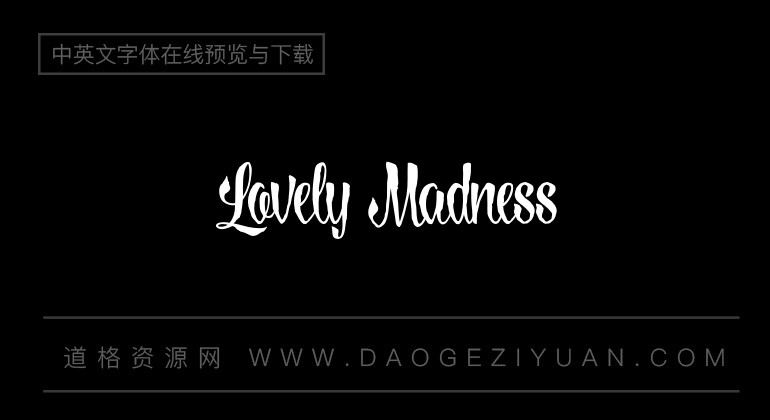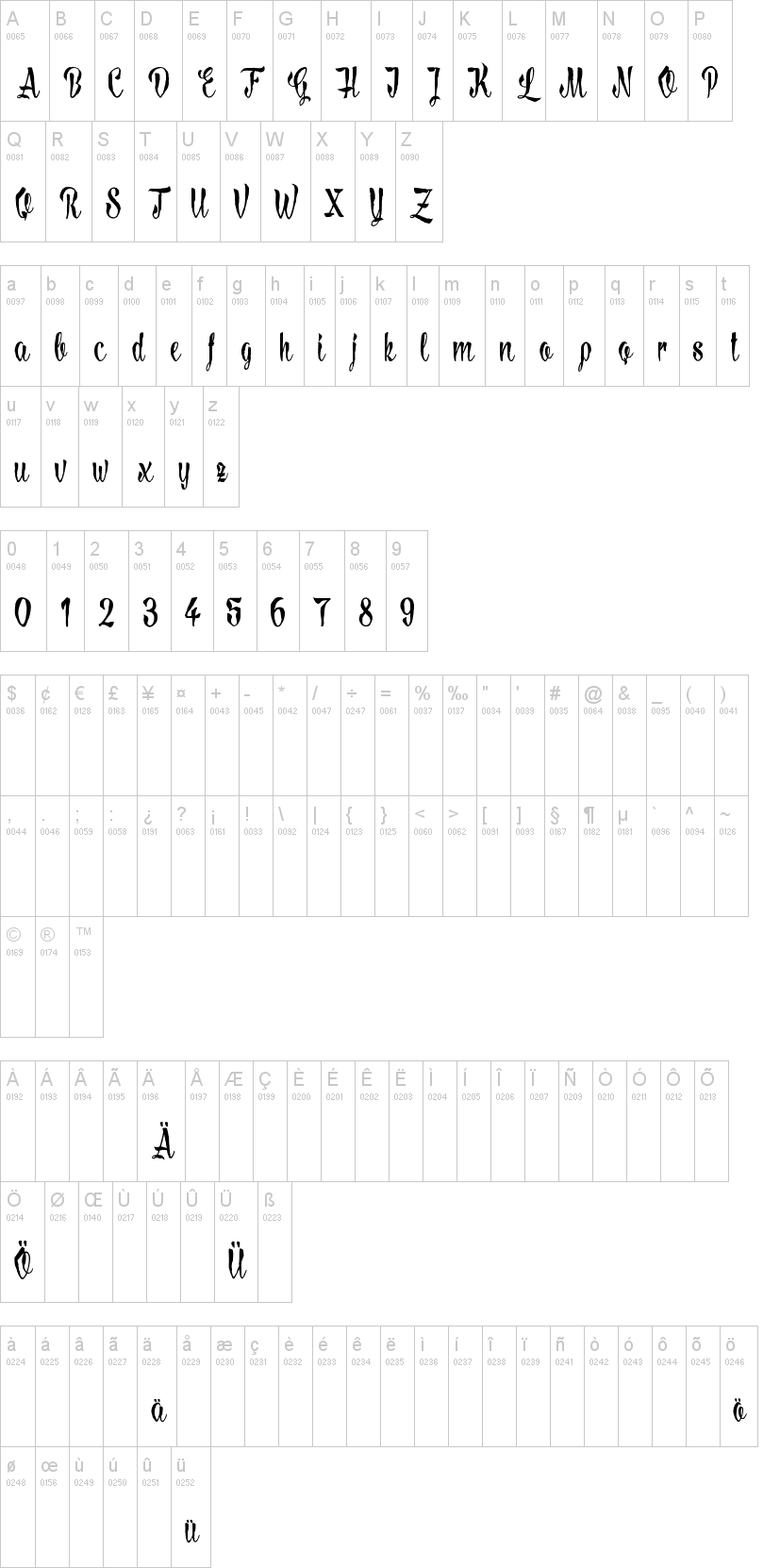
Lovely Madness
Lovely Madness 是一款由MADType设计的手写字体,它具有温暖的外观,细腻的笔画和深沉的表情,可以帮助您在设计中营造出一种温暖的氛围。它具有清晰的细节和优雅的风格,可以提供您极具设计感的文字效果。此外,它还具有多种字体样式,可以满足您的各种需求。
Lovely Madness是一款非常不错的手写艺术字体,具有很好的视觉感,适合于文化类的宣传设计、商业类品牌的广告和产品包装设计以及个性化文字排版等较多场景。
Lovely Madness字符映射图